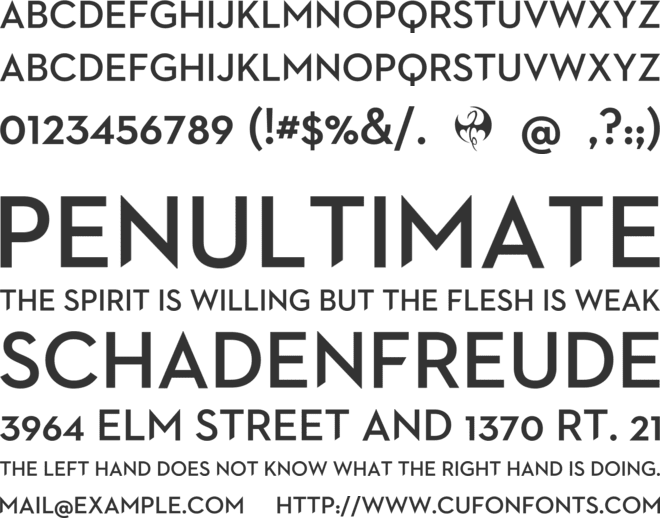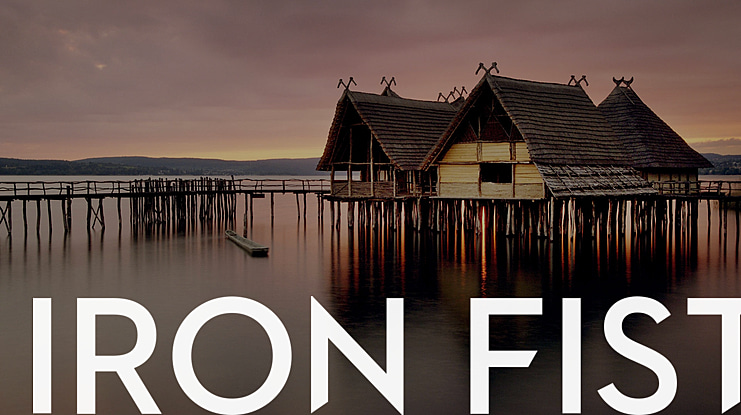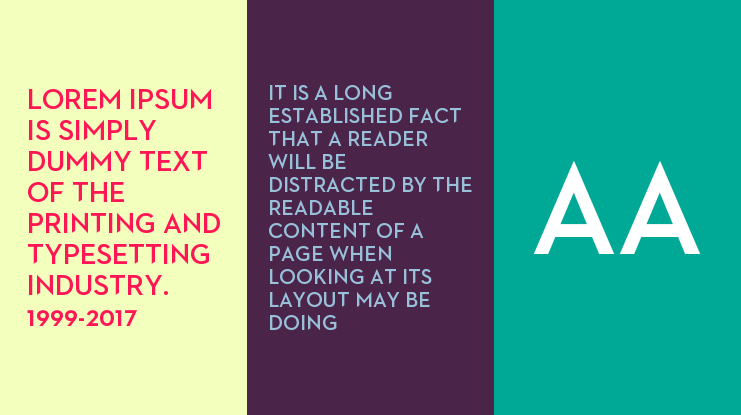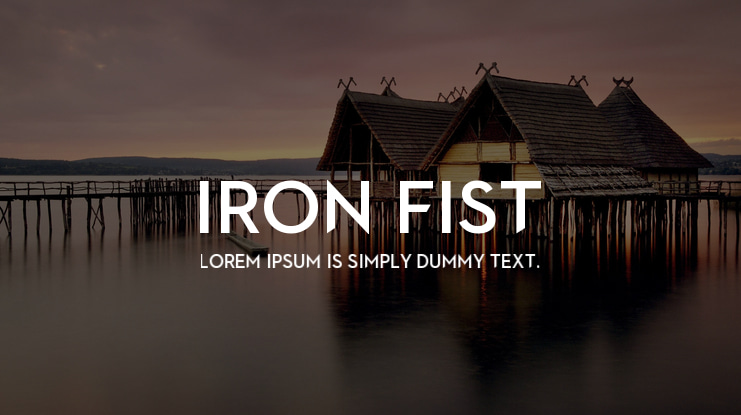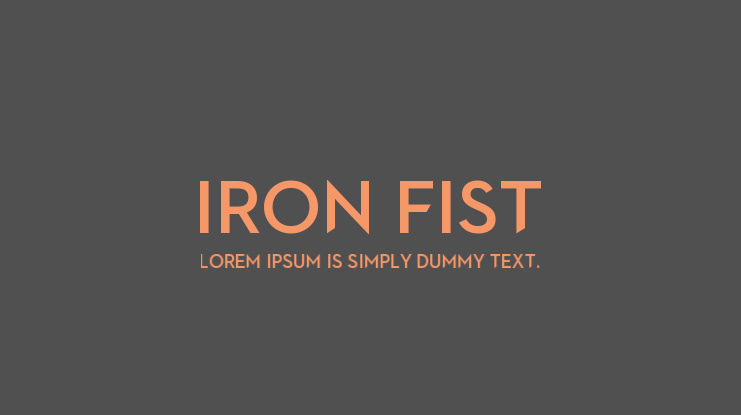
Iron Fist Font
Fuente basada en el logo de Netflix "Iron Fist" o como lo conocemos todos en español, "Puño de Hierro"
Hay signos que usted puede usar tales como:
Iron Fist en la 'o' use el signo plus +
Iron Fist en la 'o' use el signo asterisco *
Puño de Hierro en la 'o' de Puño use el signo plus +
Puño de Hierro en la 'o' de Puño use el signo asterisco *